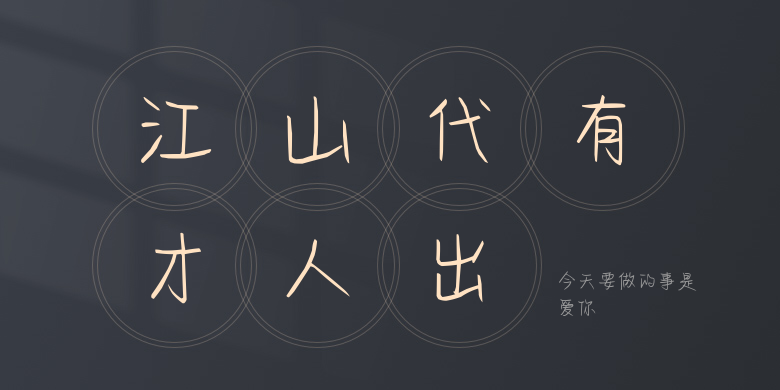
今天要做的事是爱你
今天要做的事是爱你,这款字体结构工整、笔画清晰,兼顾美观与易读性,适用于标题、正文、海报、包装、LOGO 等多种场景。字形优雅稳定,风格百搭耐看,适配日常排版与创意设计,让文字呈现更舒适、更具质感。今天要做的事是爱你一笔一画,皆是细节,以均衡的比例、流畅的线条打造舒适视觉体验,字形端正大气,风格简约现代。无论是商业设计、品牌宣传还是日常排版,都能轻松驾驭,让文字更有格调与力量。今天要做的事是爱你字体下载。